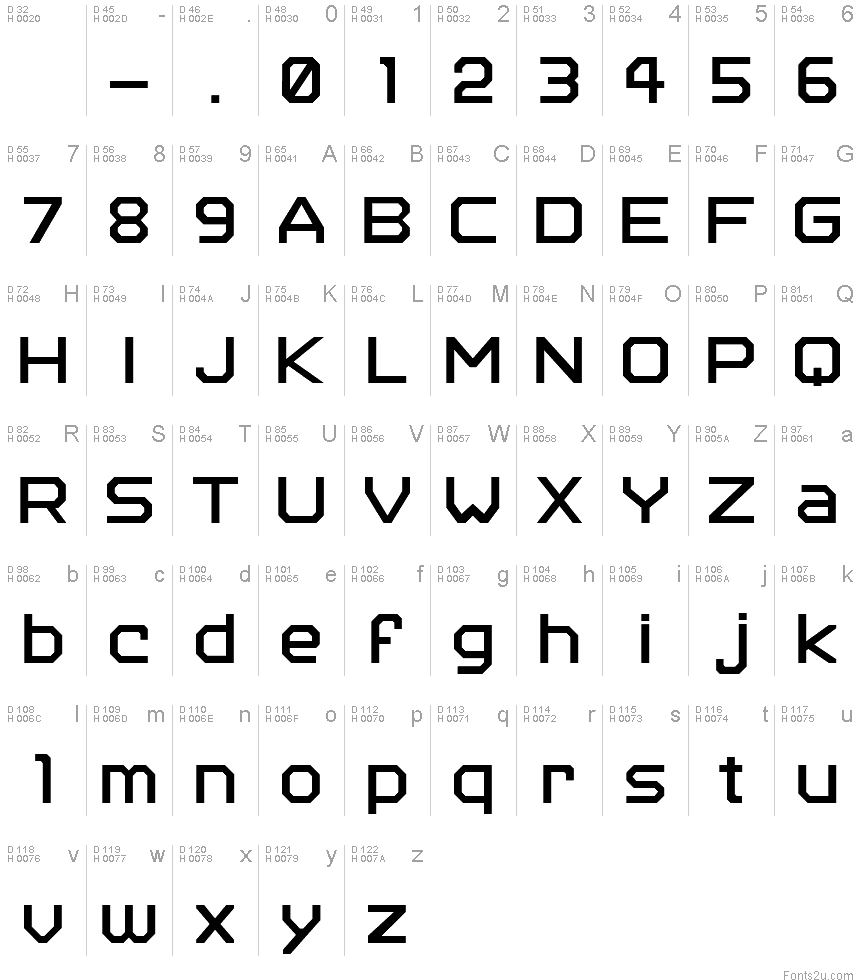
Spaceport
Supe-se que Spaceport 2006 foi uma srie sci-fi britnica rodada em 1976 e concebida por um cineasta sem talento querendo se valer da crescente popularidade do gnero.
Kitsch e de efeitos precrios, a srie teria sua continuidade cancelada aps poucos episdios, passando dcadas no esquecimento. No sculo XXI, um grupo de entusiastas descobriram novamente a srie que ganharia status de cult graas divulgao via internet, tornando-se, posteriormente, um cone do gnero.
SpacePort a fonte empregada em todo este suposto projeto visual da srie. Um deleite para os amantes de sci-fi de baixo oramento.